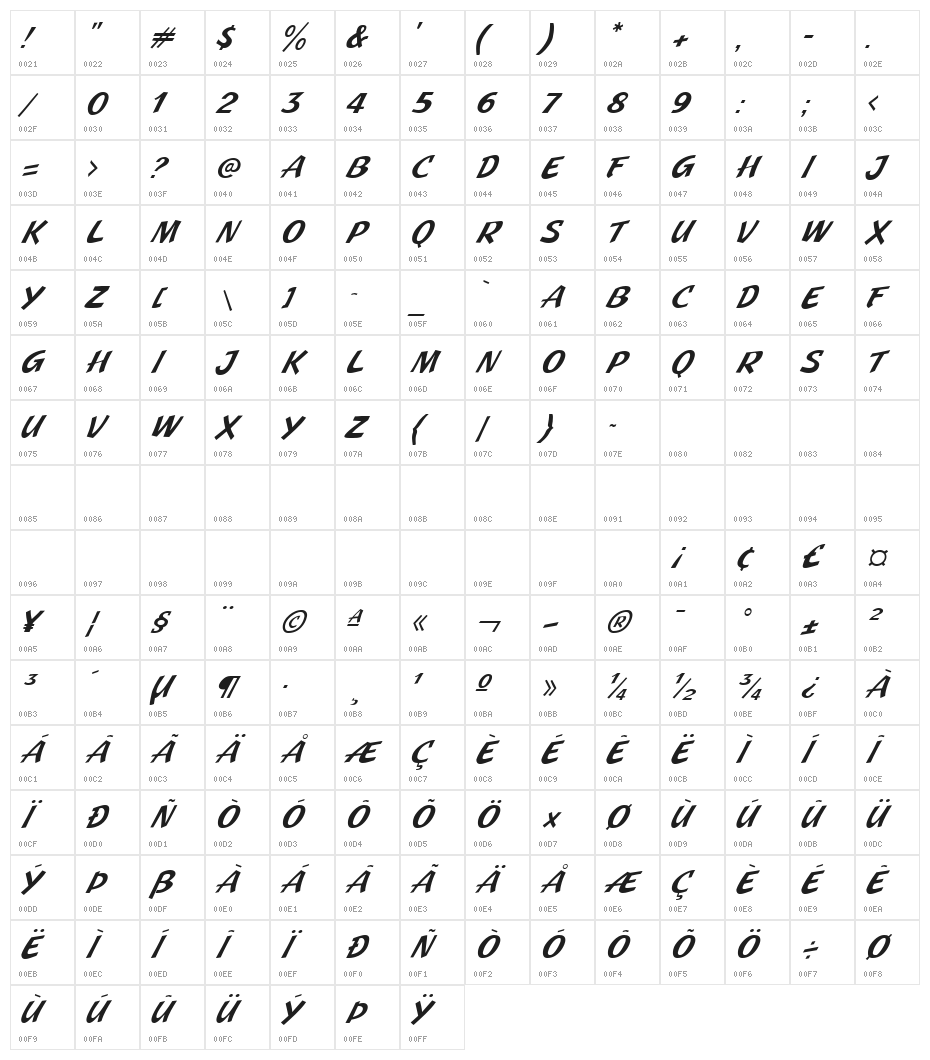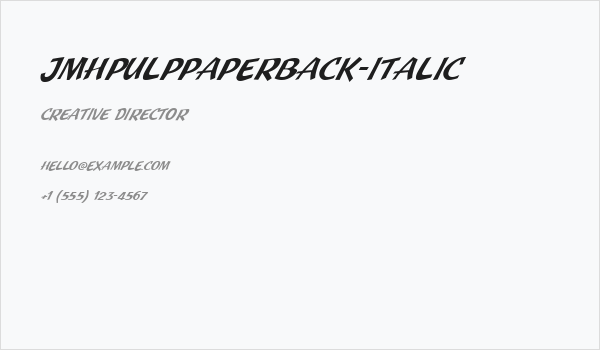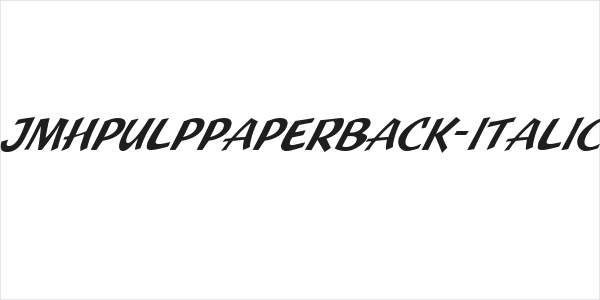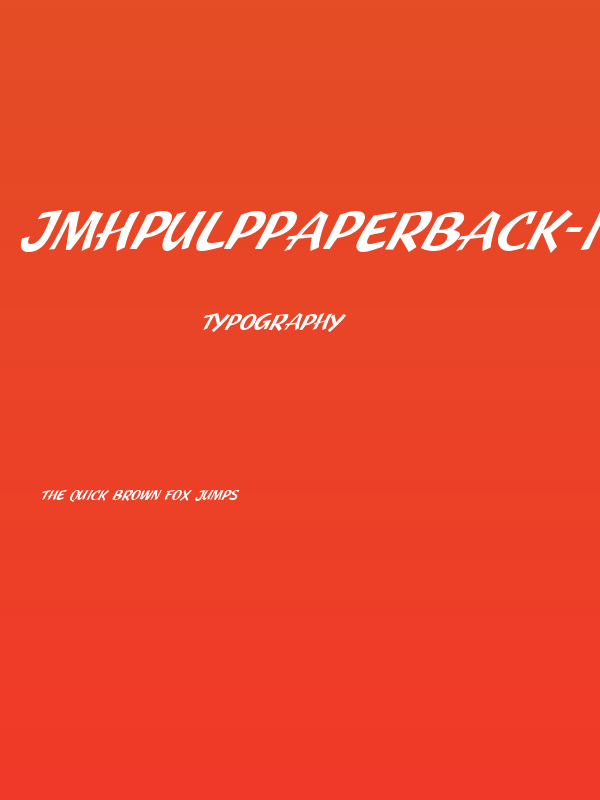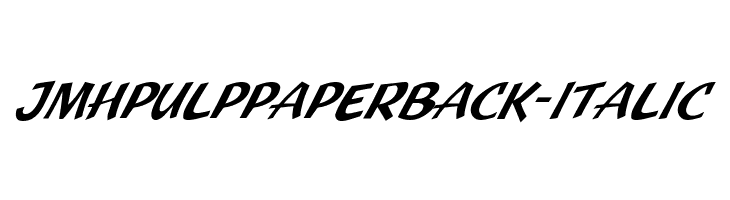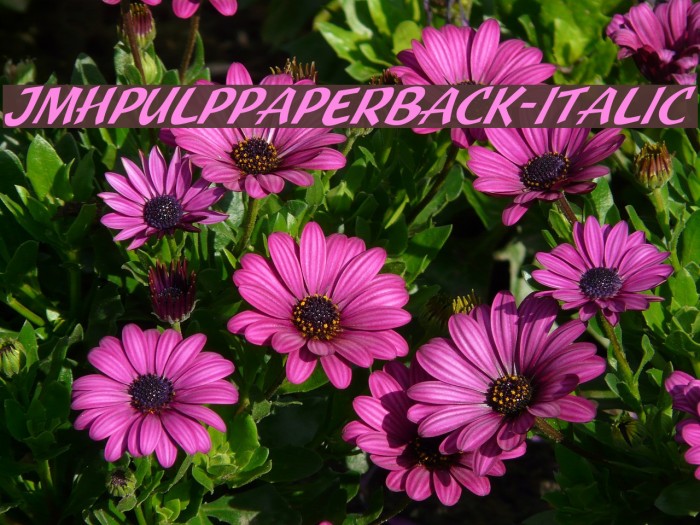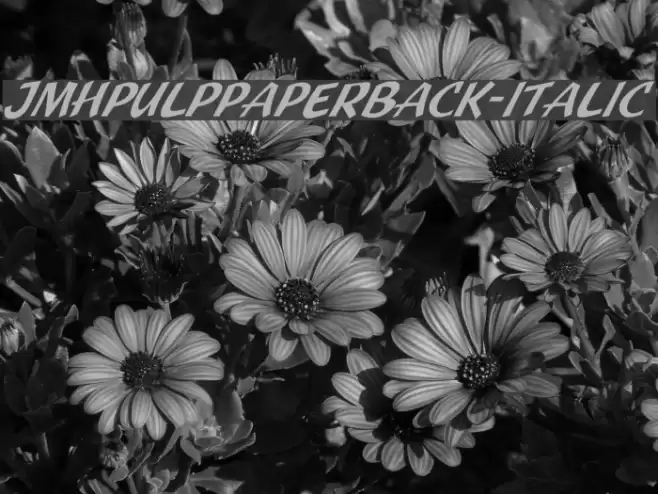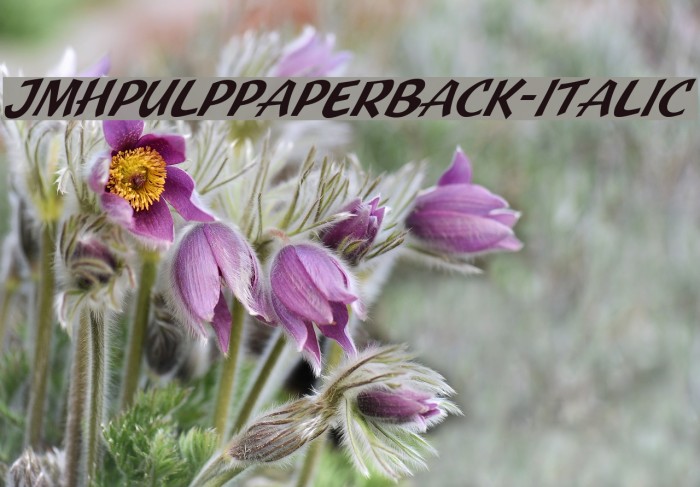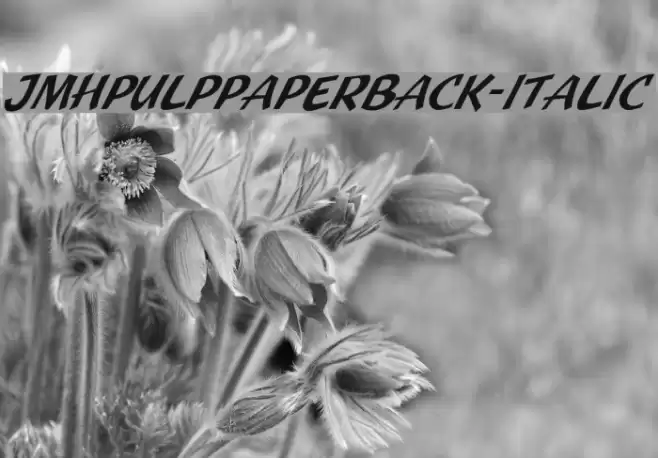
JMHPulpPaperback-Italic Font
| Projets proposés | Ideal for book covers, posters, branding materials, and any design needing a bold, dynamic typeface. |
| Auteur | Fonts by Måns Grebäck |